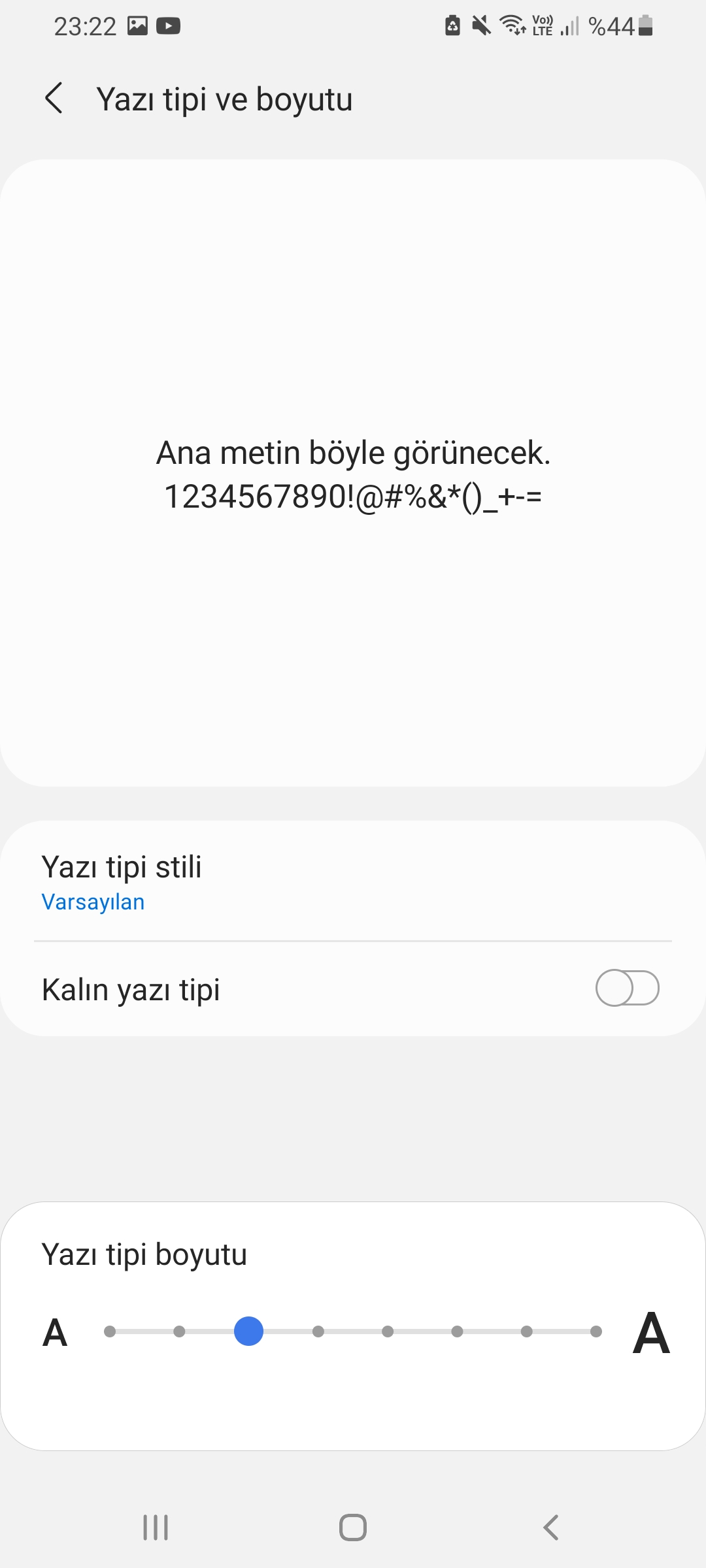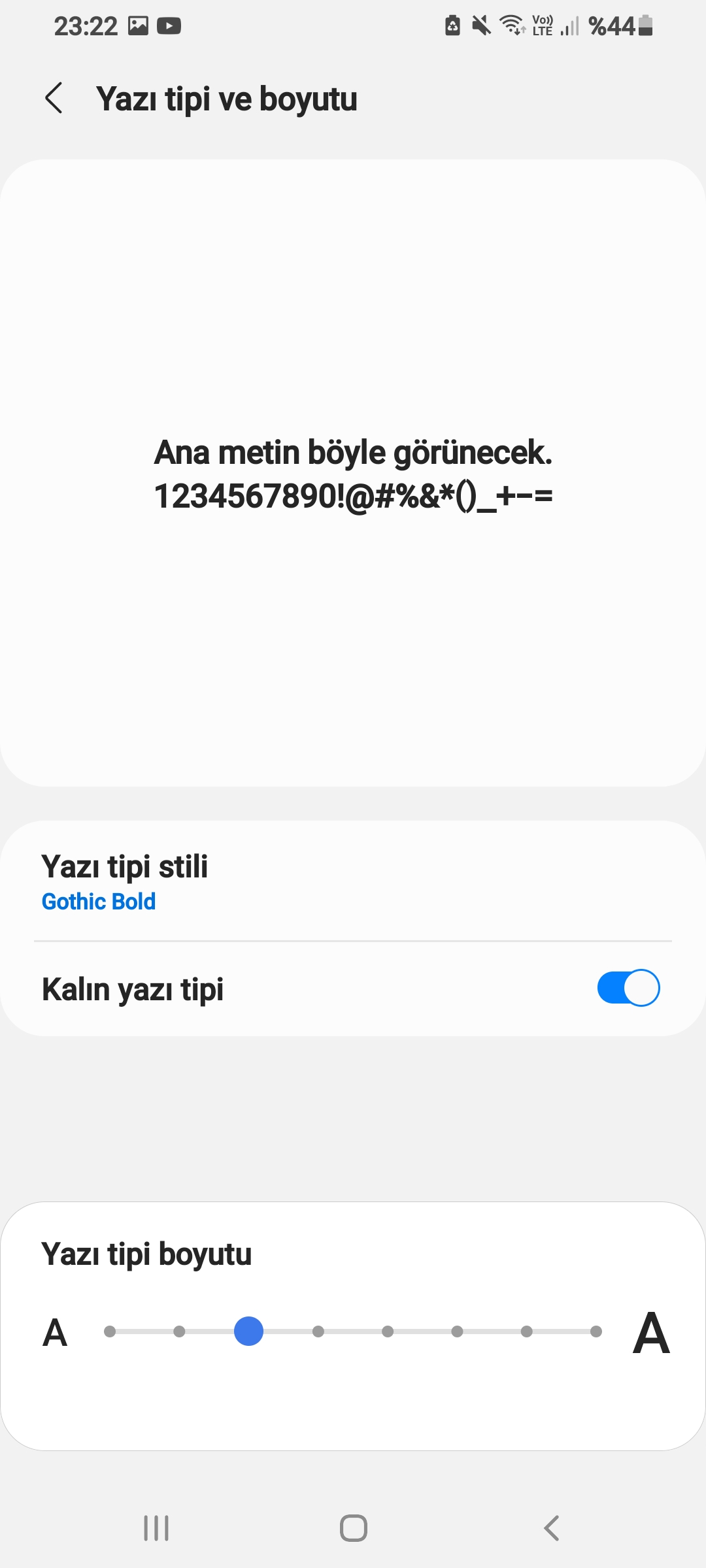
Hangi yazı tipi daha iyi
Merhaba hocalarım aşağıya eklediğim 2 fontdan hangisi daha iyi acaba 🙏
Hangi website script ve dizaynında kullanacaksınız?
İnce daha iyi